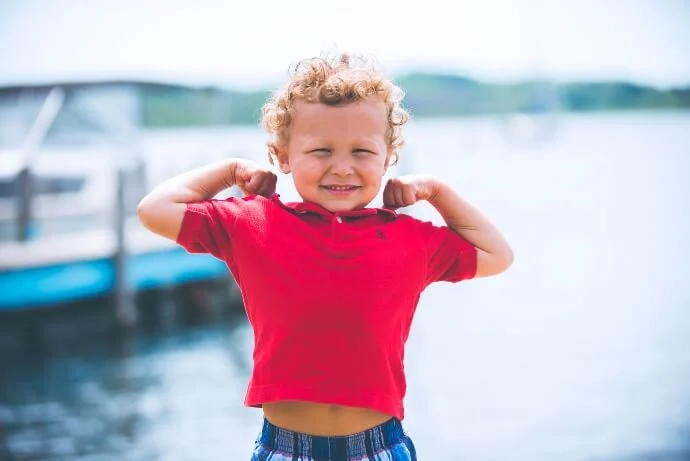
Die richtigen Schriftarten und Farben für Ihr nächstes Ferrari-rotes Poloshirt
Erwägen Sie die Anschaffung eines roten Ferrari-Poloshirts für die Mitarbeiter Ihres Unternehmens oder einfach zum Tragen im Alltag, vielleicht in Kombination mit einem schwarzen Rock oder einer schwarzen Hose?
Und wenn die Personalisierung auch einen Text beinhaltet, müssen Sie auch an die perfekte Schriftart denken, damit das Endergebnis bis ins kleinste Detail stimmt.
Eine Farbe, die nicht zu einem Ferrari-roten Poloshirt passt, und die falsche Schriftart könnten den Reiz dieses Kleidungsstücks zerstören.
Das wollen wir auf keinen Fall, deshalb geben wir Ihnen heute wichtige Tipps zur Auswahl der richtigen Schriftart und Farbe für Ihren Druck oder Ihre Stickerei . So können Sie Ihre eigenen, preiswerten Polo-Shirts individuell gestalten und hervorragende Ergebnisse erzielen!
Rotes Ferrari-Poloshirt: Auswahl der Schriftart für den individuellen Text
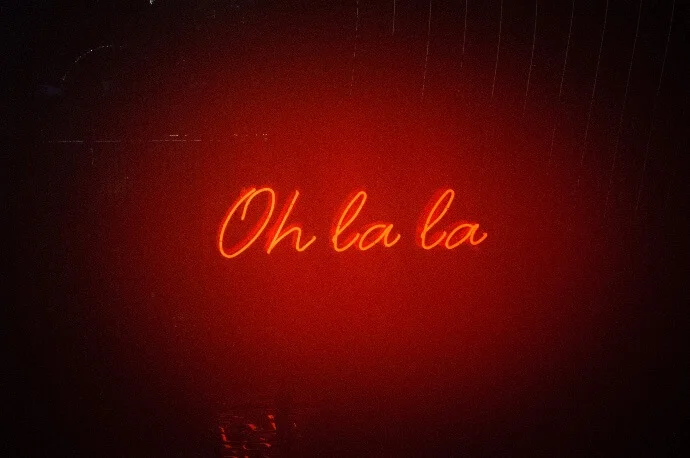
Bei individuellen Beschriftungen für Textilien empfehlen wir in der Regel serifenlose Schriftarten . Schlichte Schriftarten lassen die Wörter gut zur Geltung kommen, trennen die einzelnen Buchstaben klar voneinander und lenken die Aufmerksamkeit des Lesers nicht ab.
Sie machen auch kleinste Texte lesbar, was mit einer Serifenschrift sonst schwierig wäre.
Ein weiterer Tipp: Schreiben Sie in Druckbuchstaben, die Schreibschrift eignet sich eher für preiswerte, individuell gestaltete schwarze oder weiße T-Shirts .
Eine auf ein rotes Ferrari-Poloshirt gedruckte Schreibschrift wäre praktisch unleserlich, da es keine Farbe gibt, die einen so guten Kontrast wie Weiß auf Schwarz und umgekehrt bietet.
Fettdruck hingegen kann eine gute Idee sein, insbesondere wenn Sie eine Schriftart verwenden, die einen großen Abstand zwischen den Buchstaben aufweist.
Die richtige Farbe für den Schriftzug auf Ihrem roten Ferrari-Poloshirt
Um ein perfektes Endergebnis zu erzielen, ist die Wahl der richtigen Farbkombination unerlässlich.
Wir raten von der Verwendung von Lila, Braun oder Grün ab, da diese Farben nicht gut zu einem Ferrari-roten T-Shirt oder Poloshirt passen, weil sie nur wenig Kontrast bieten.
Die perfekte Kombination für Ihren Text, der auf das Poloshirt gedruckt oder gestickt werden soll, könnte eine der folgenden sein:
- Rot und Weiß
- Rot, Weiß und Blau
- Rot, Orange und Gelb
Schauen wir uns im Folgenden an, warum wir diese Kombinationen gewählt haben.
Rotes Ferrari-Poloshirt mit weißer, individueller Beschriftung
Diese Farbkombination ist eine hervorragende Wahl für einen modernen und trendigen Look. Details kommen am besten zur Geltung, wenn ein starker Kontrast zwischen der Druckfarbe und dem T-Shirt-Stoff besteht.
Aus diesem Grund wirkt ein aufgedrucktes oder gesticktes Weiß auf einem leuchtend roten Poloshirt absolut perfekt, ebenso wie ein weißes Poloshirt mit rotem Aufdruck. Der Kontrast zwischen den beiden Farben ist so stark, dass jeder Text klar lesbar ist.
Rotes Ferrari-Poloshirt mit weißer und blauer Schrift
Wer sagt denn, dass Schriftzüge einfarbig sein müssen? Tatsächlich ermöglicht die Verwendung von zwei verschiedenen Farben, den endgültigen Effekt noch vielseitiger zu gestalten.
Das Farbschema Rot, Weiß und Blau passt hervorragend zu jeder Art von Design oder Schriftzug. Die Primärfarben Rot und Blau harmonieren gut mit der Neutralität von Weiß.
Rotes Ferrari-Poloshirt mit orangefarbenen und gelben Akzenten
Die warme Farbkombination aus Rot, Orange und Gelb eignet sich auch hervorragend für ein individuell gestaltetes Poloshirt. Diese Farben ergeben in Kombination wunderschöne und dynamische Designs.
Orange mag zwar nicht viel Kontrast erzeugen, aber es ermöglicht Ihnen , gelbe Schrift auf eine wirklich originelle Weise zu schattieren.
Um zusammenzufassen…
Hier ist, was Sie für die Anfertigung eines hervorragenden, individuell gestalteten Ferrari-roten Polo-Shirts benötigen:
- Die perfekte Schriftart: serifenlos und mit gut lesbaren Buchstaben. Am besten in Blockschrift, damit jeder die Aufschrift auf Ihrem Poloshirt problemlos erkennen kann.
- Die richtigen Farben. Beschränken Sie sich nicht auf Rot und Schwarz, sondern erkunden Sie andere Farbkombinationen: Rot und Weiß, Rot, Orange und Gelb sowie Rot, Weiß und Blau.